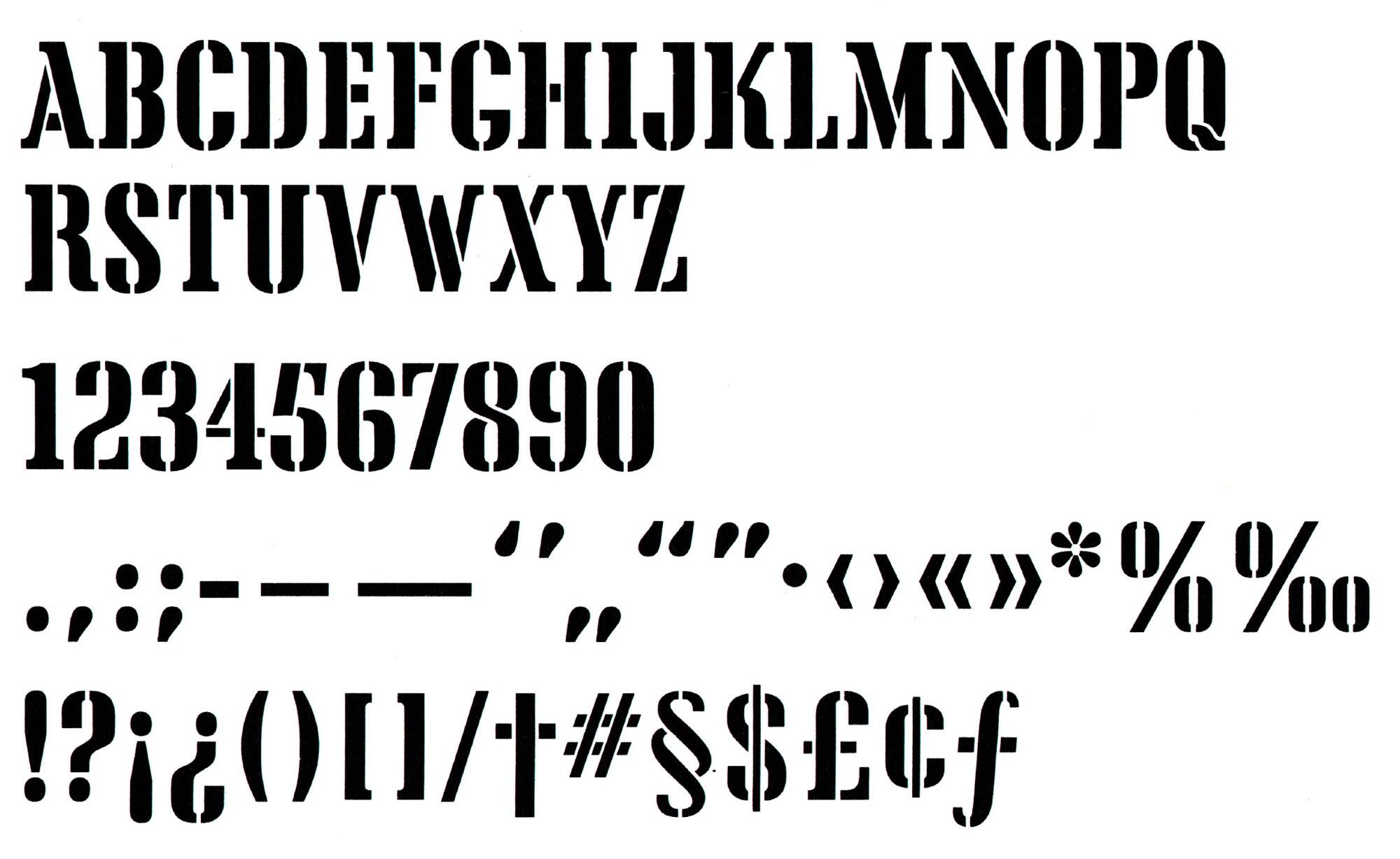
- 1937
- Antiqua dekorativ
Die Schablonenschrift Tea Chest von Robert Harling erschien in den 1930er-Jahren bei Stephenson Blake als reines Versalalphabet.